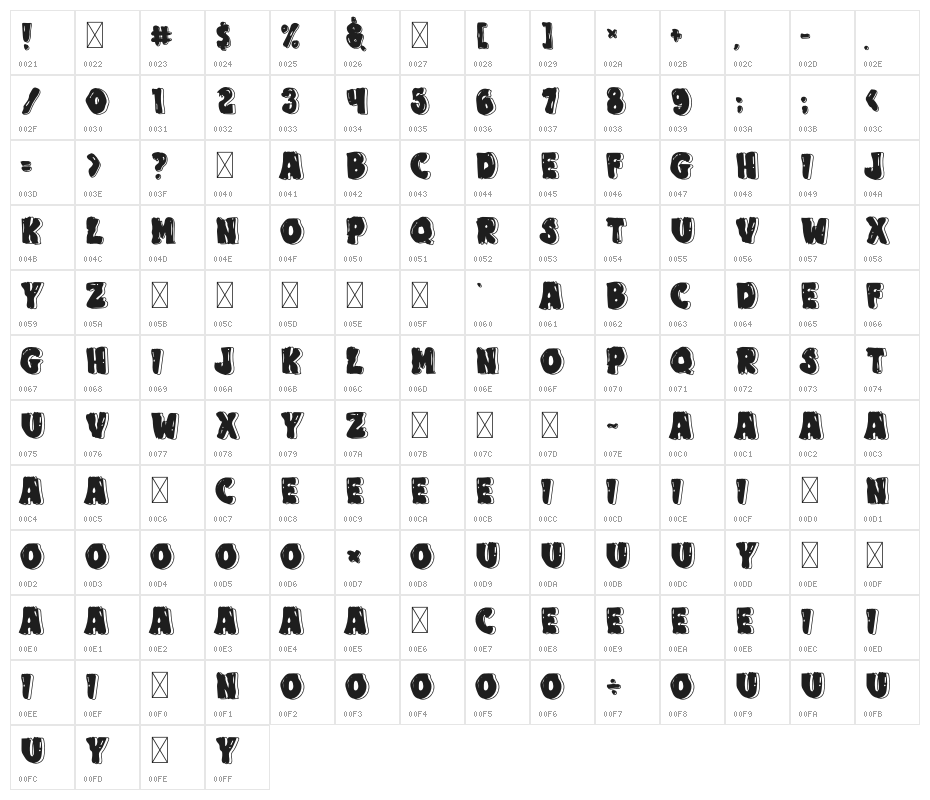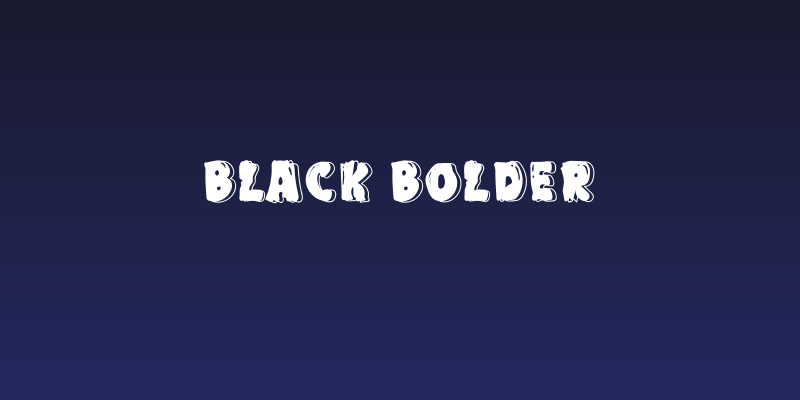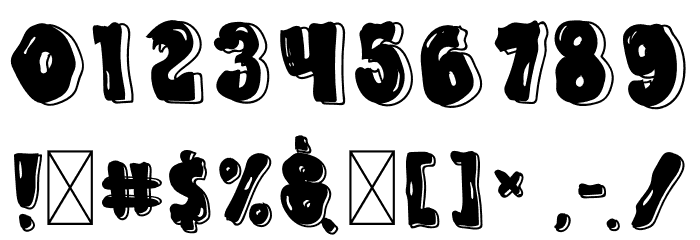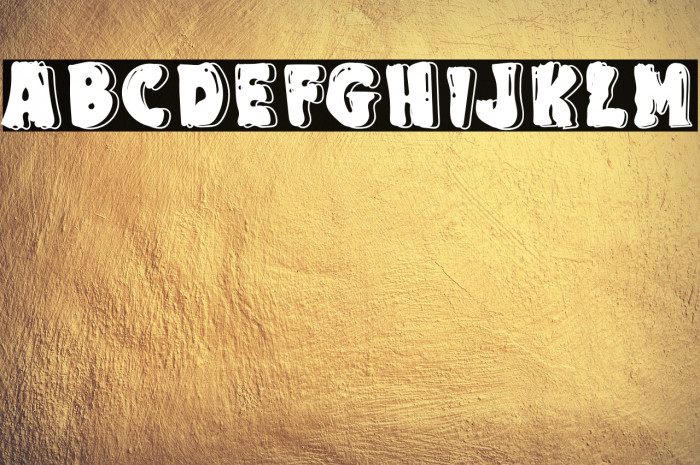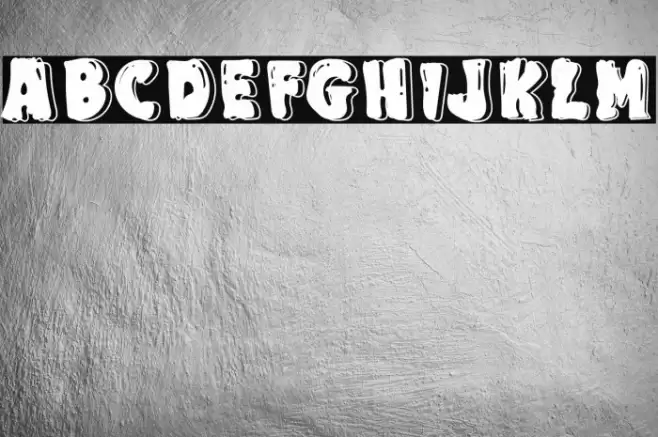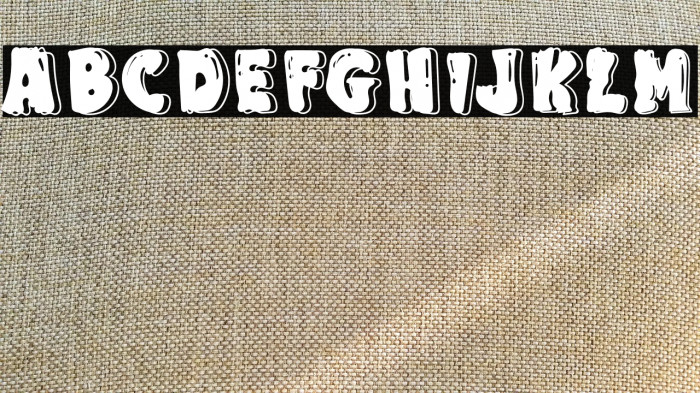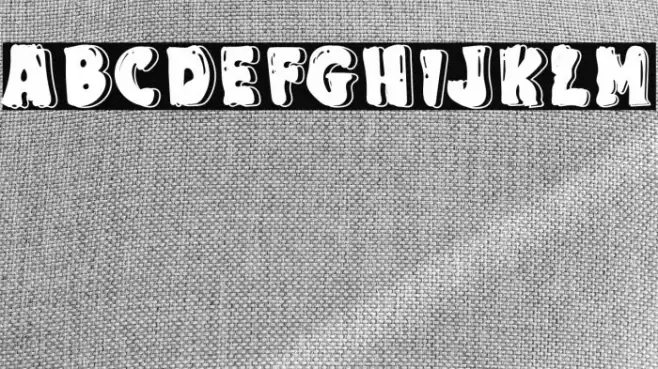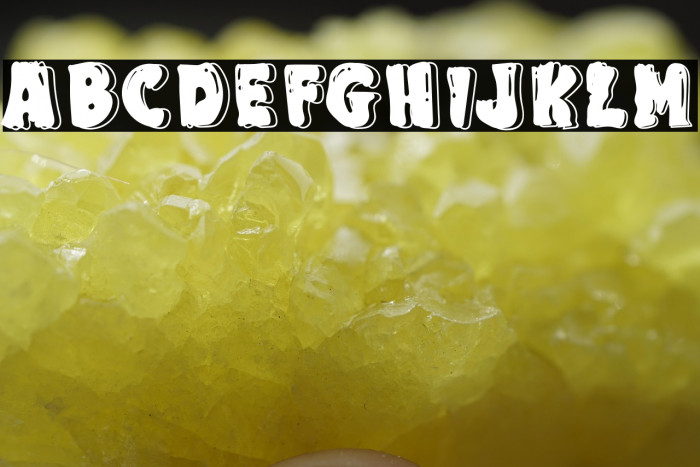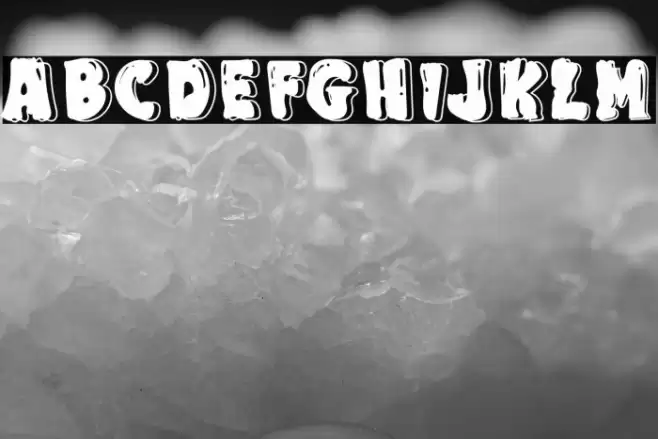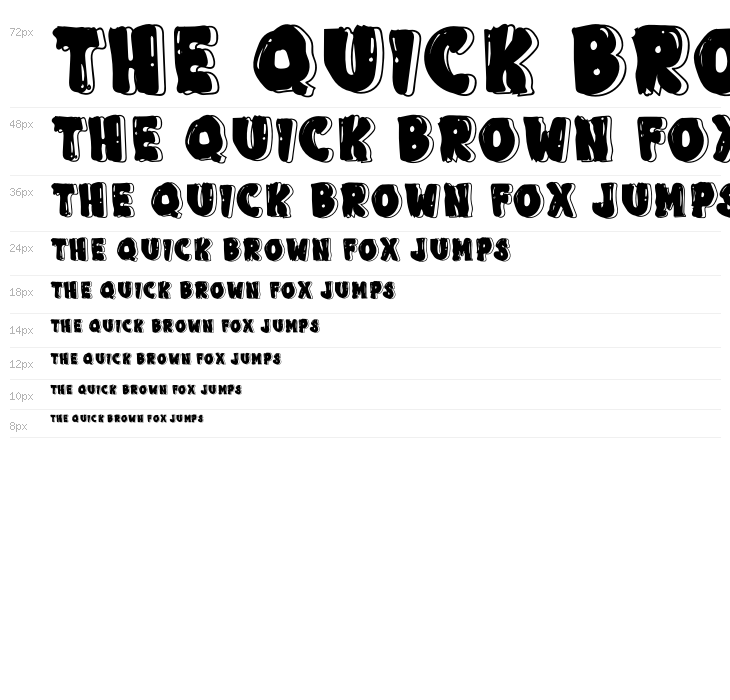
BLack Bolder Font
| Stil general | Playful, Whimsical, Cartoon-like |
| Caz de utilizare | Headlines, Posters, Invitations |
| Proiecte propuse | Ideal for children's books, playful posters, party invitations, and eye-catching headlines. |